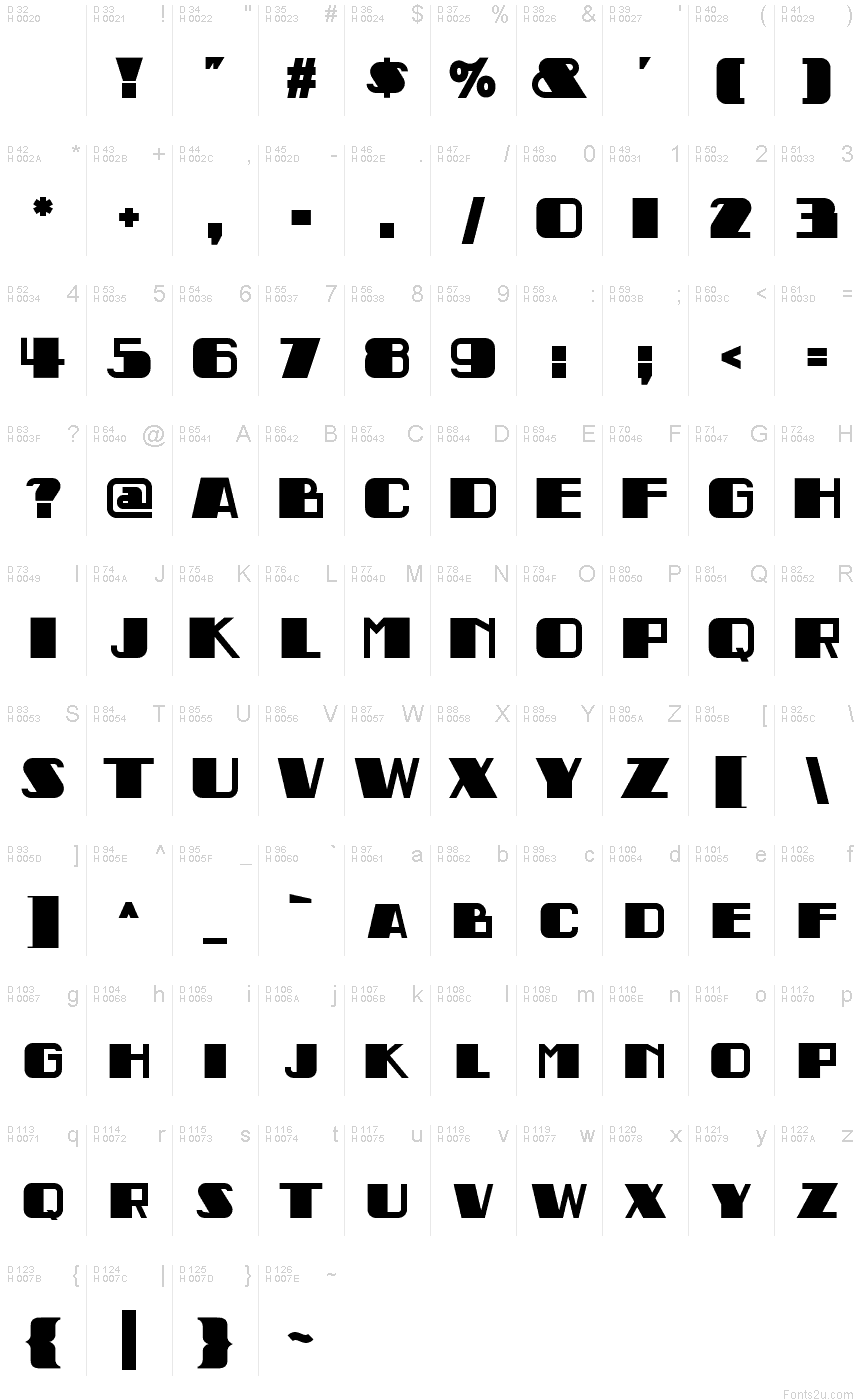
خط Indochine NF من تصميم Nick Curtis هو خط عرض ريترو مجاني يبدو مثل كتلة من الحبر على ورق الملصقات. الأشكال المربعة الثقيلة والقصات الحادة تمنحه طابعاً وحشياً يشبه القوالب الجاهزة (Stencil)، بينما تخلق المسافات المتقاربة شعاراً بصرياً كثيفاً وسينمائياً من النظرة الأولى. يبدو الخط خشناً وعصرياً، تماماً مثل العناوين المطبوعة على ملصقات أفلام الأكشن القديمة أو ملصقات المنتجات المستوردة الكلاسيكية.
يتألق هذا الخط المجاني على الملصقات الجريئة، ومنشورات النوادي الليلية، وأغلفة الأسطوانات، وهويات العلامات التجارية لملابس الشارع أو البارات، والعناوين التحريرية اللافتة للنظر. عند استخدام Indochine NF بأحجام كبيرة، تبرز هندسته الضخمة وتفاصيله المنحوتة؛ قم بإقرانه بخط sans serif بسيط في النصوص الصغيرة للحفاظ على وضوح التصميم بينما تظل العناوين هي محور الاهتمام.